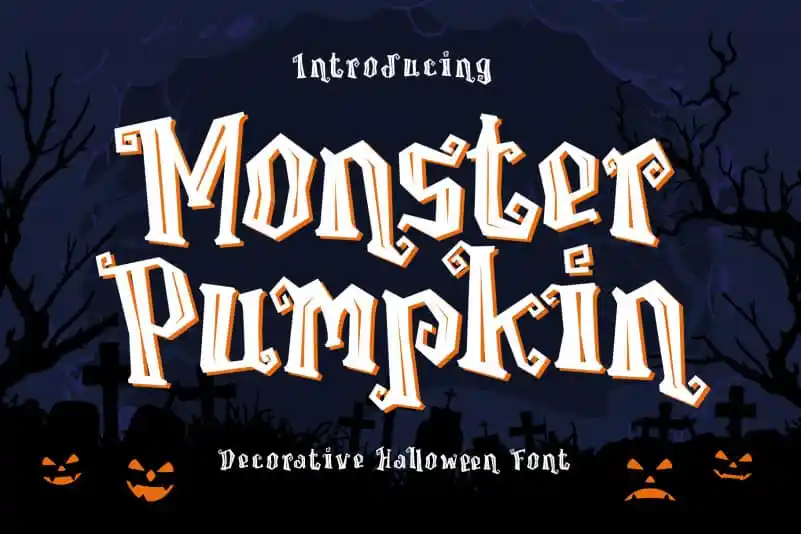
Monster Pumpkin Display Font – Download Grátis
A fonte ‘Monster Pumpkin Display Font’ é perfeita para decorar sua festa de Halloween com estilo assustador. Criada para complementar a celebração do Dia das Bruxas, essa font é forte e poderosa, combinando elementos de horror e medo. É ideal para criar posters ou folhetos de Halloween, deixando seu evento ainda mais impactante e memorável. Seja você um criador de conteúdo, designer gráfico ou até mesmo a organizadora da festa, ‘Monster Pumpkin Display Font’ é a escolha certa para traduzir suas ideias assustadoras em design visível. Sua capacidade única de criar textos temáticos com o tema das Halloween torna essa font uma excelente adição à sua coleção de recursos gráficos.